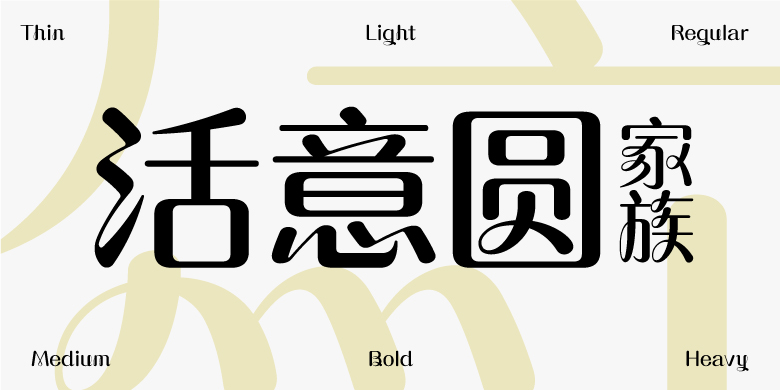
方正活意圆家族
方正活意圆家族,这款字体结构工整、笔画清晰,兼顾美观与易读性,适用于标题、正文、海报、包装、LOGO 等多种场景。字形优雅稳定,风格百搭耐看,适配日常排版与创意设计,让文字呈现更舒适、更具质感。方正活意圆家族一笔一画,皆是细节,以均衡的比例、流畅的线条打造舒适视觉体验,字形端正大气,风格简约现代。无论是商业设计、品牌宣传还是日常排版,都能轻松驾驭,让文字更有格调与力量。方正活意圆家族字体下载。
《方正活意圆家族》是粗活意的姊妹之作,一款充满动感的字体,所有转弯的部分都用柔线牵动,充满柔和飘逸感受,采用圆体造型表达后,更充满柔和温馨的感受,适合男女高档品牌、时装美容、珠宝首饰行业,高端酒店和房地产宣传的商业百搭字体。